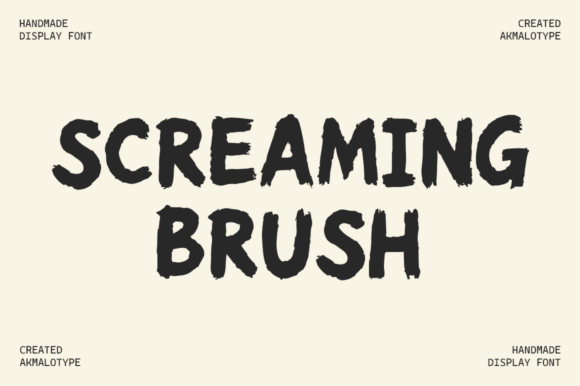
Screaming Brush
Dibuat dengan presisi, Screaming Brush menyediakan vektor yang bersih, tipografi yang halus, serta lisensi komersial untuk ketenangan pikiran Anda.
Baik Anda membuat produk POD (Print on Demand), undangan pernikahan, atau grafis media sosial, Screaming Brush adalah pilihan yang sangat ideal.